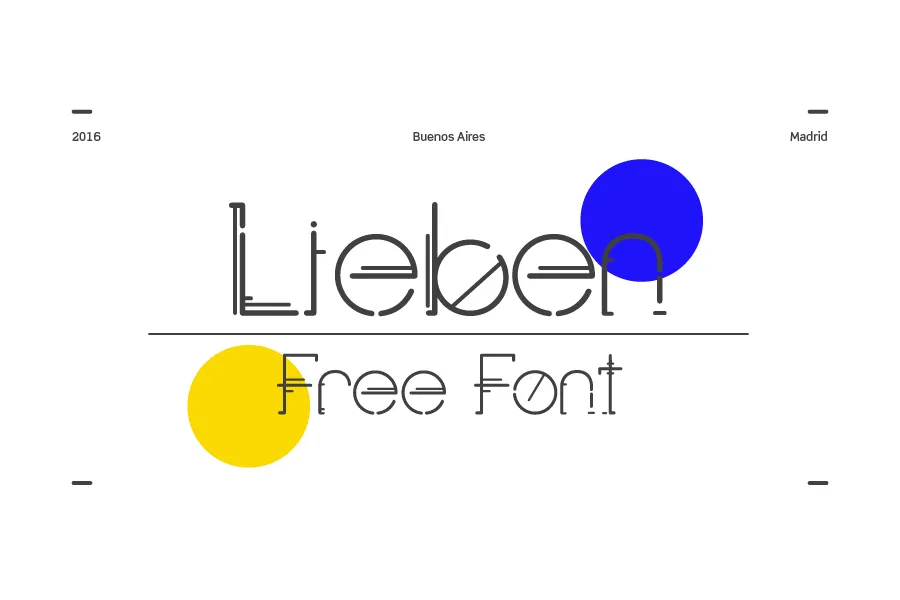
Lieben Font – Download Grátis
A Lieben Font é uma elegante e sofisticada tipografia de destaque, criada pelo designer Hamilton. Com suas linhas arredondadas e formas geométricas harmoniosas, ela combina perfeitamente com designs modernos e minimalistas que valorizam a simplicidade do visual. Essa fonte é ideal para aplicações onde deseja destacar o texto em um modo mais chamativo. Ela se mostra especialmente útil em anúncios publicitários, portais de notícias digitais e até mesmo em materiais de marketing digital, como banners e peças promocionais. Sua simplicidade faz com que seja fácil ler, mas sua presença visual garante um impacto inegável. A Lieben Font é perfeita para quem procura uma solução pronta para uso, sem ter que ajustar muito a aparência do texto ou a aparência geral da página em que ela está inserida. Além disso, esta fonte combina bem com qualquer estilo de design moderno e minimalista. É a escolha perfeita para aquelas criações digitais que buscam equilíbrio entre funcionalidade e presença visual impressionante.